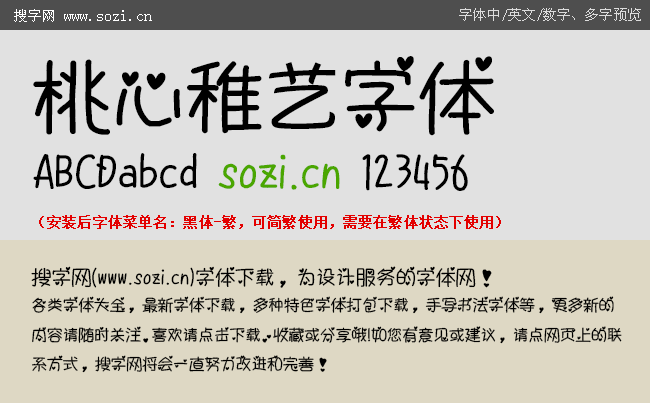
桃心稚藝體(ST Heiti-Medium)
搜字網(wǎng)提供一款可愛(ài)卡通風(fēng)格的手機(jī)中文字體下載,名叫桃心稚藝體,這款手機(jī)字體以稚藝體為原形,在字體中嵌入了卡通心形圖案,稚藝體非常漂亮,帶有卡通風(fēng)味,活潑而不死板,加入卡通圖案后更加活潑可愛(ài)。喜歡的朋友就下載吧。